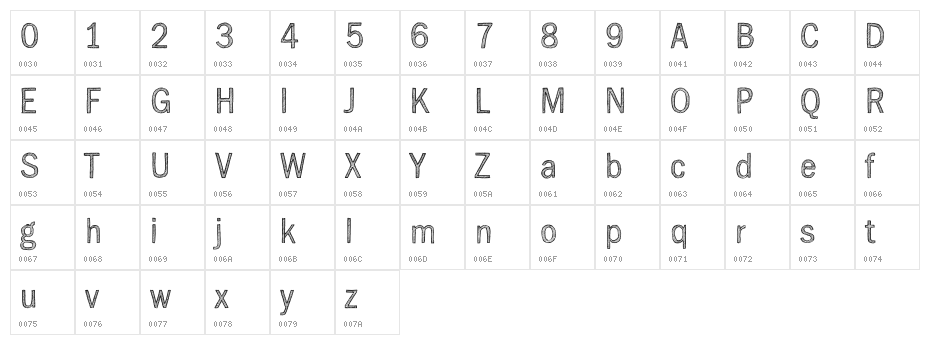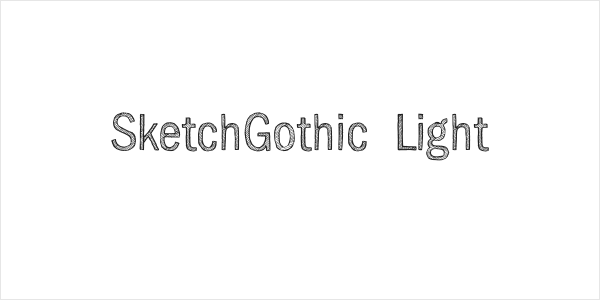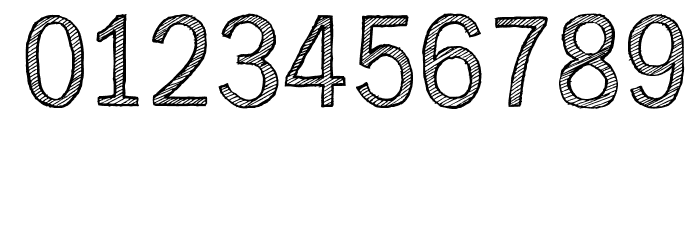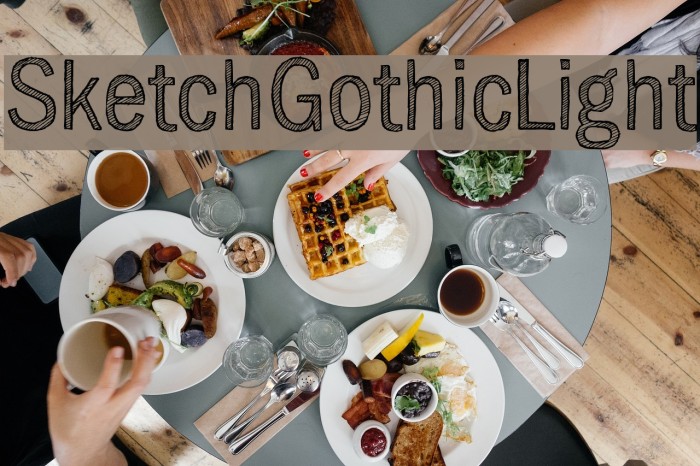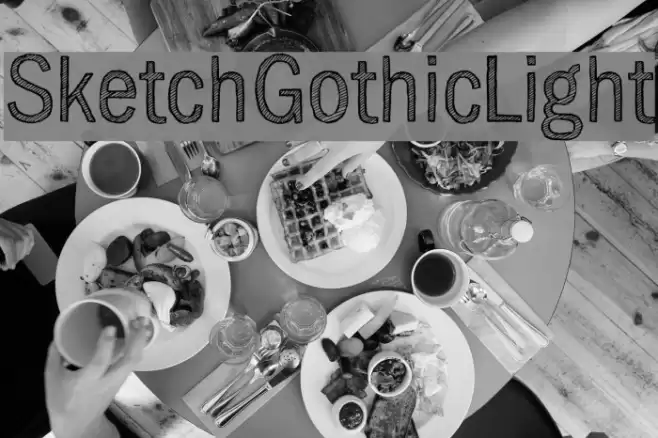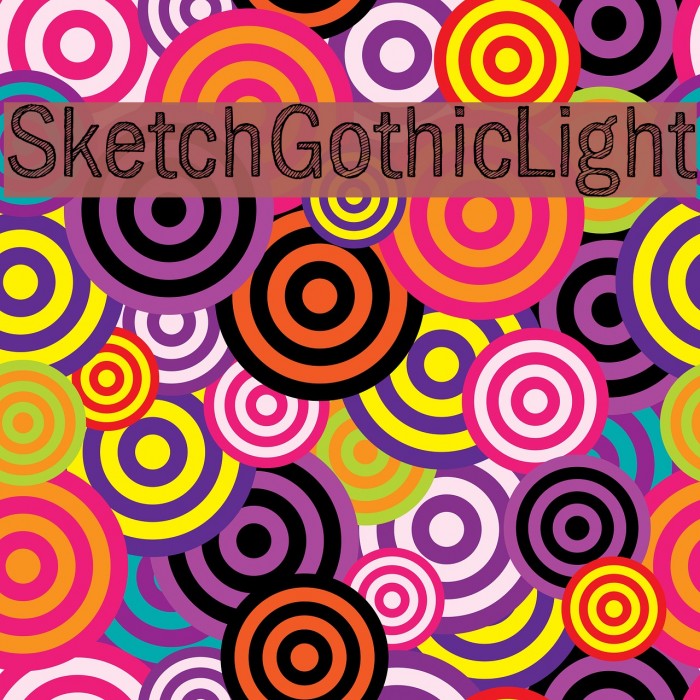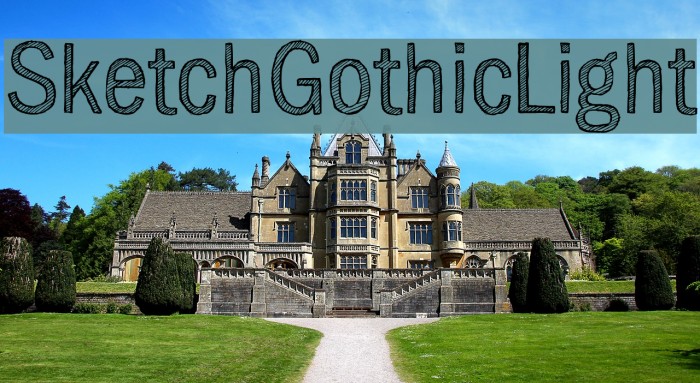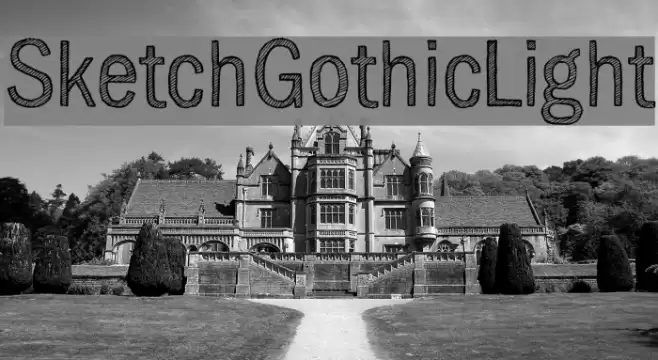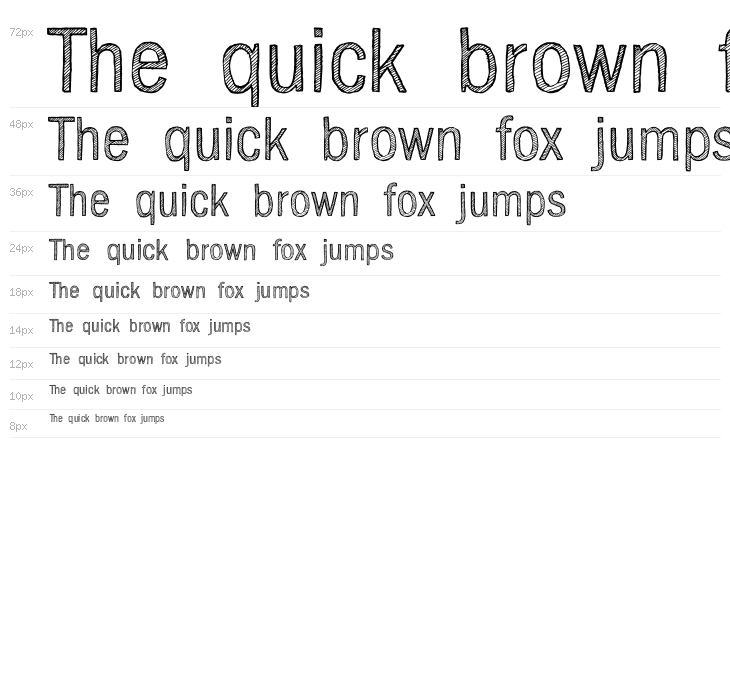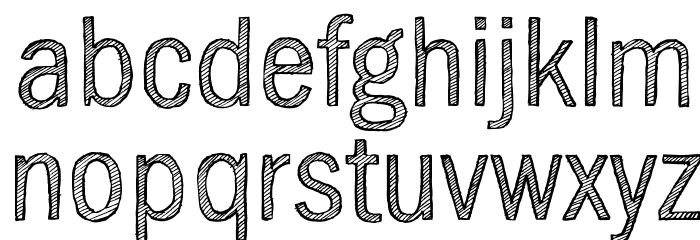
SketchGothic-Light Font
| Stile generale | Artistic, Playful |
| Caso d'uso | Headlines, Posters, Branding |
| Progetti proposti | Ideal for creative projects such as posters, invitations, children's books, and branding materials that require a casual and artistic touch. |